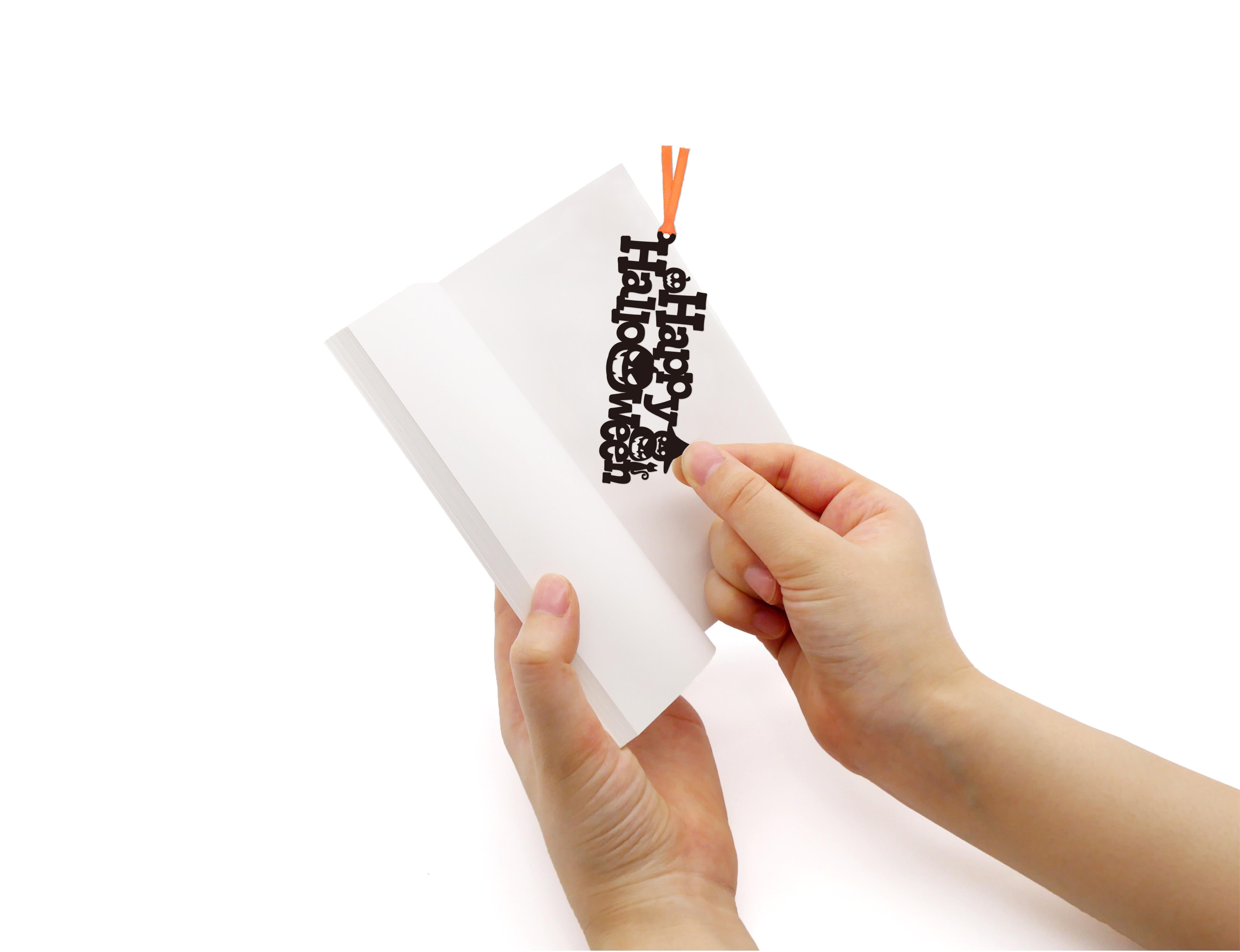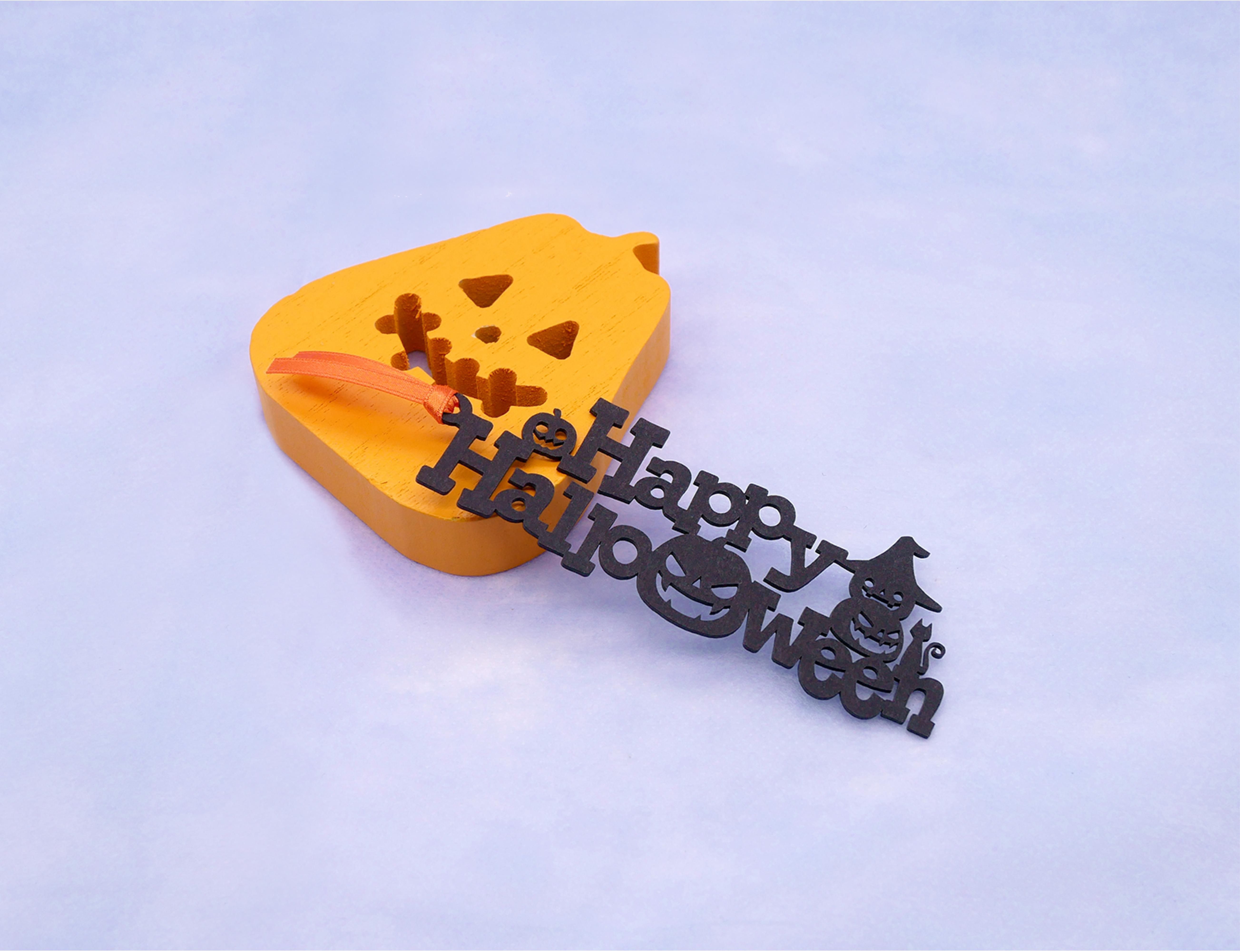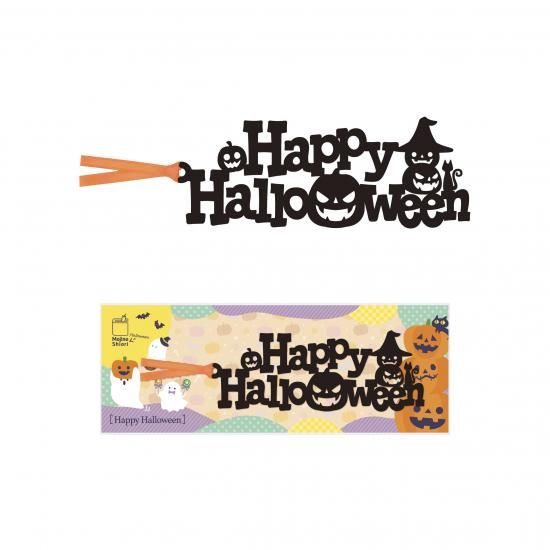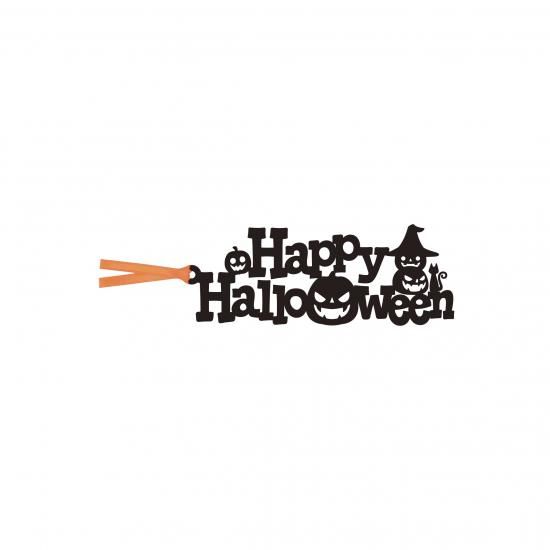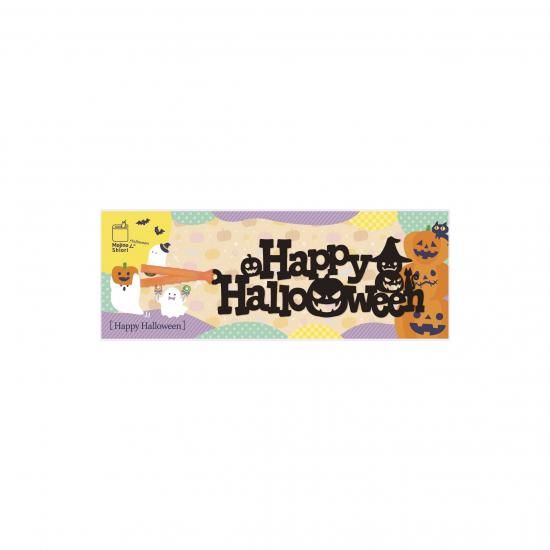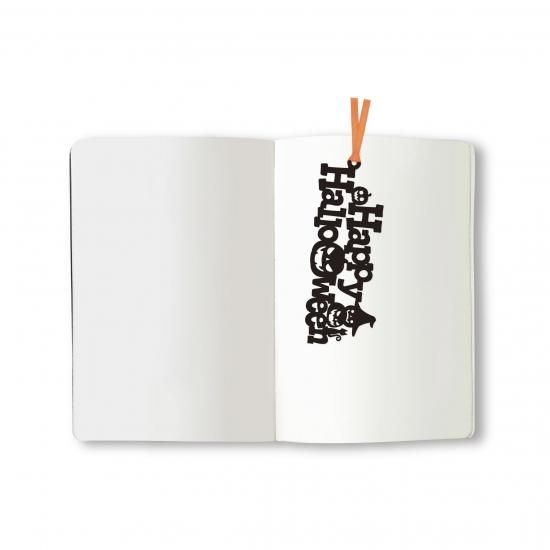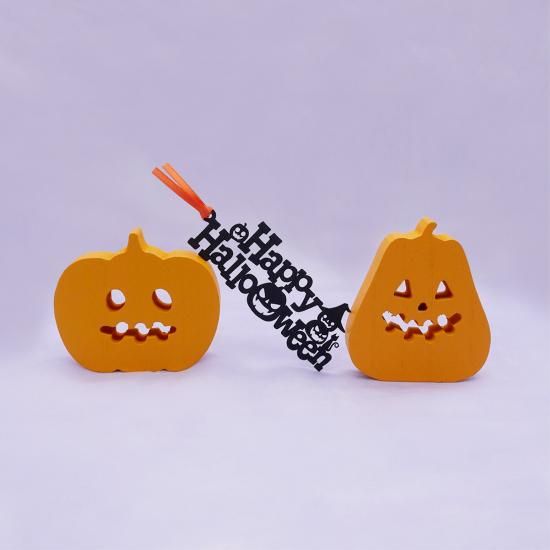
【期間限定】文字のハロウィンのしおり「Happy Halloween」
お化けと一緒に文字のしおりも、トリック・オア・トリート!?
文字のしおりシリーズにキュートでスリリングな「文字のハロウィンのしおり」が期間限定の登場です!
ハロウィンのちょっとした贈り物として、遊び心を添えたサプライズとして、ドキドキワクワク、魔法の世界へレッツゴー!ハロウィンムードを一気に盛り上げます。
読書タイムをよりスペシャルに。世界がもっとハッピーでありますように。
大切な人と一緒に、キュートでスリリングな文字のハロウィンのしおりの魔法をお楽しみください!
本好きの方、お城好きの方にはもちろん、ちょっとした贈り物としても喜ばれそうです。